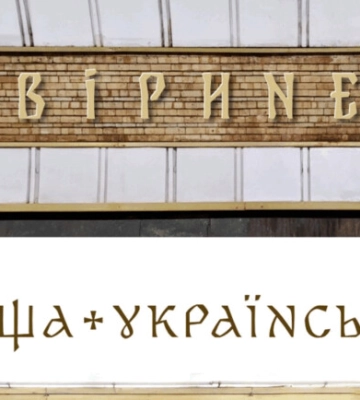
На перейменованих станціях метро у Києві використають у написах новий шрифт
Останнім часом у Києві йдуть перейменування топонімів, зокрема станцій метрополітену. Поки що на станціях висять старі написи, проте вже розроблено нові. Нагадаємо, у травні в Києві станцію метро "Площа Льва Толстого" було перейменовано на "Площу Українських Героїв". Також станцію метро "Дружби народів" було перейменовано на…